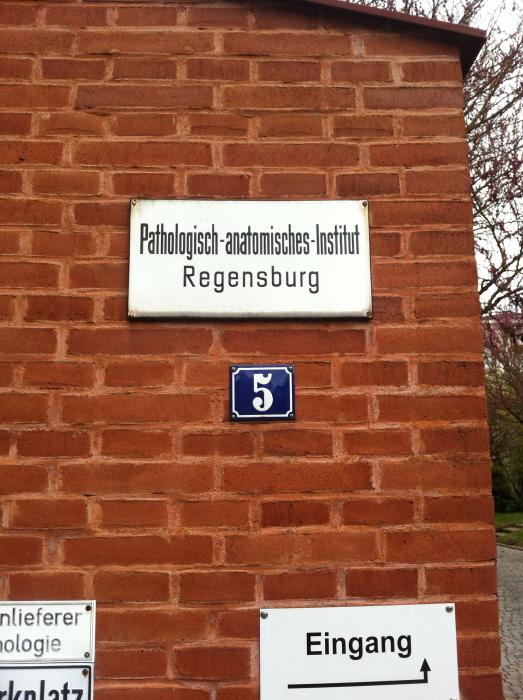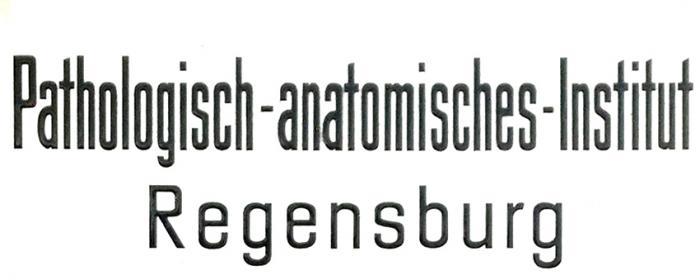
Tolle 20er Jahre Schrift auf Firmenschild
kann mir jemand sagen, was das für eine Schrift sein könnte? Viel von ihrem Charme liegt wahrscheinlich auch an der Handarbeit des Schildermachers...
Oh, sehr cool!! Die passt schon ziemlich gut . Danke!!